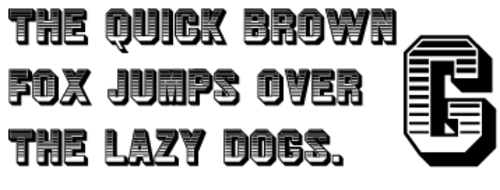
| カテゴリ | 画面 |
| 分類 | グロテスクなサンセリフ |
| デザイナー | 未知 |
| 鋳造所 | ディキンソン活字鋳造所 |
| 再発行ファウンドリ | ATF、ロサンゼルスタイプファウンドリー、スカイラインタイプファウンドリー |
ジム・クロウは、アメリカン・タイプファウンダーズが1933年と1949年に、ディキンソン・タイプファウンドリーの1850年代の書体ゴシック・シェードを鋳造し直したものである。ボストンの書体鋳造所であるディキンソンは、1892年の最初の合併でATFに組み入れられていた。この書体はトゥームストーンとも呼ばれていた。ATF はこの書体を24ポイントでしか鋳造しなかったが、ロサンゼルス・タイプファウンドリーによる後のバージョンでは18ポイントから30ポイントで鋳造された。[1] この書体は政治的なモチーフを示すためによく使われた。コールドタイプ版は1970年代を通じて人気があったが、大手の鋳造所はデジタル版を発行しておらず、今日ではほとんど使用されていない。ファウンドリーのハロルド・フォントは、ジム・ダンディというデジタル版をリリースした。[2]